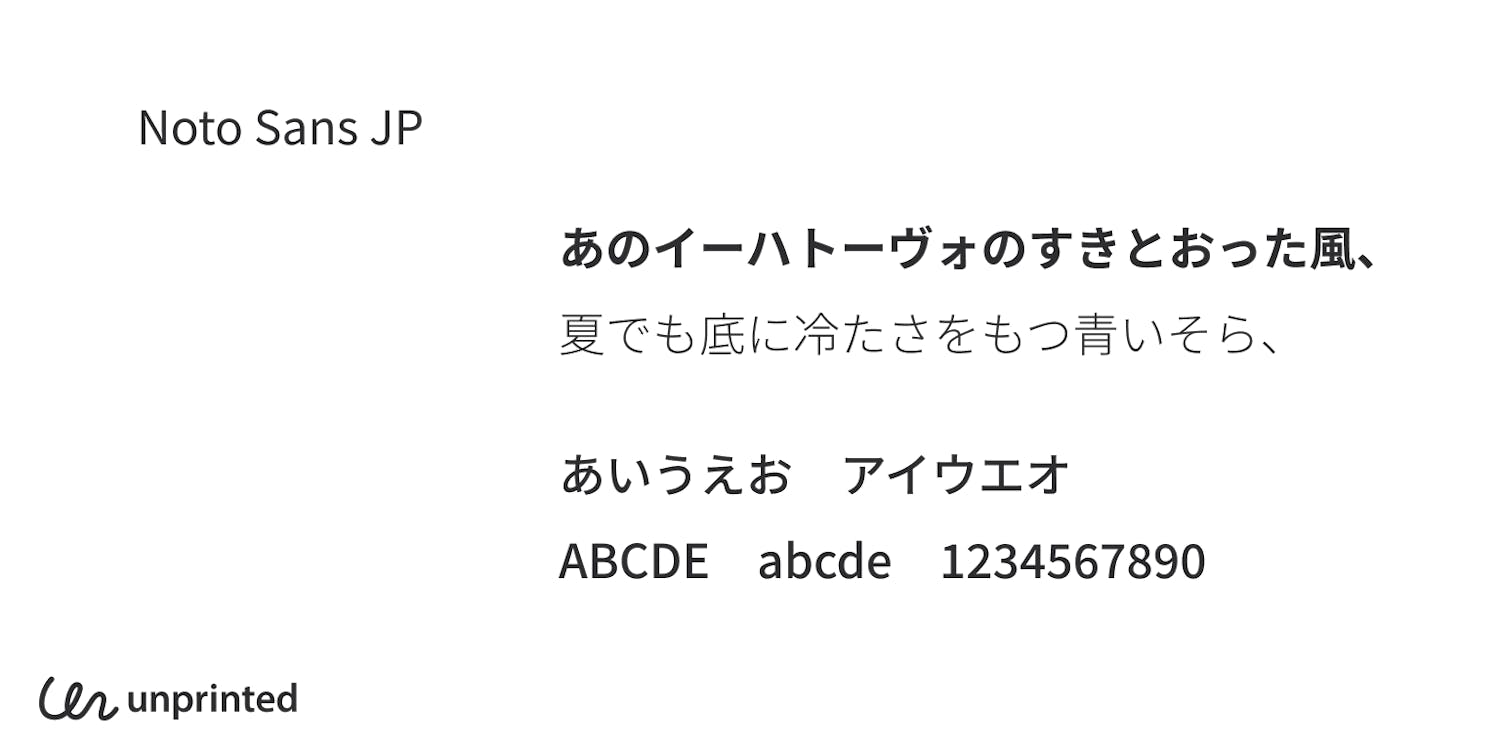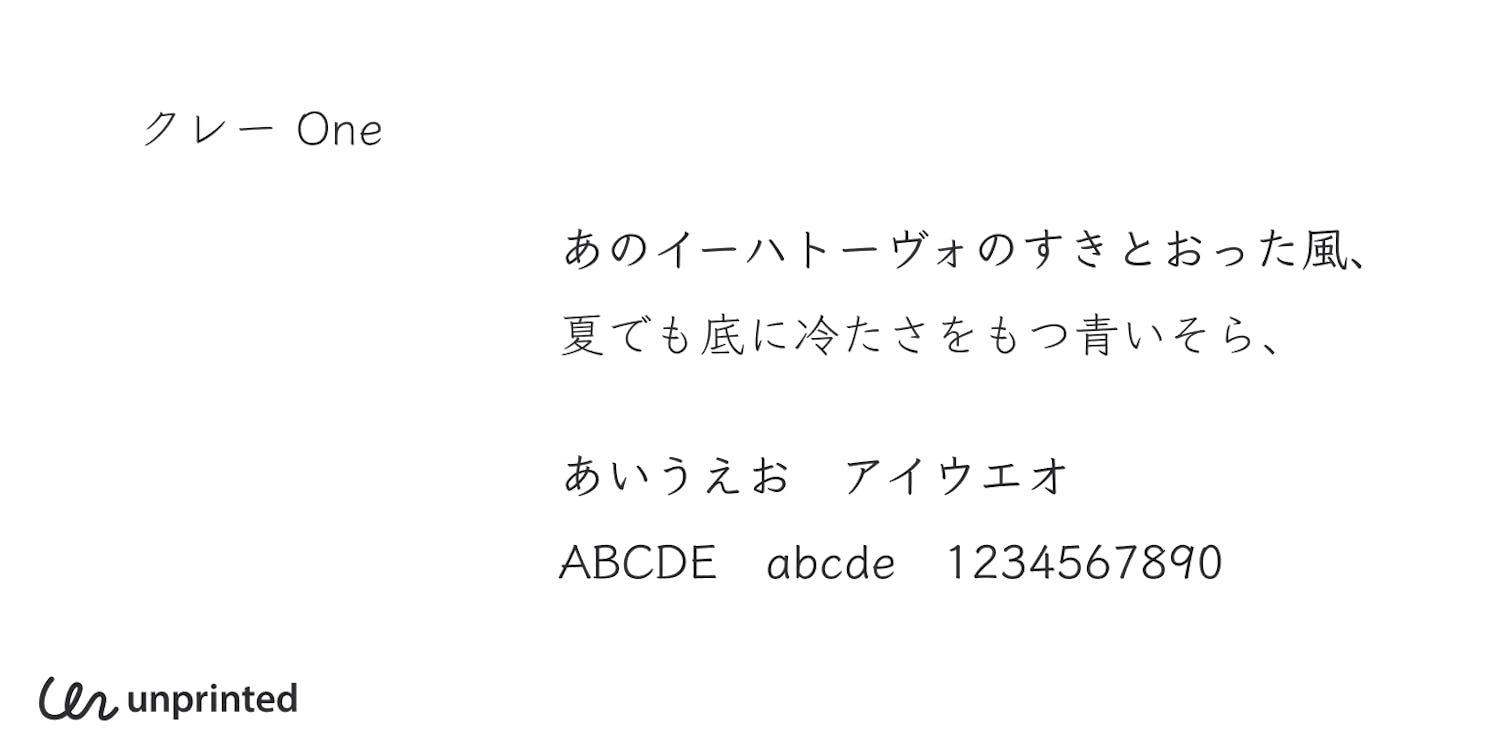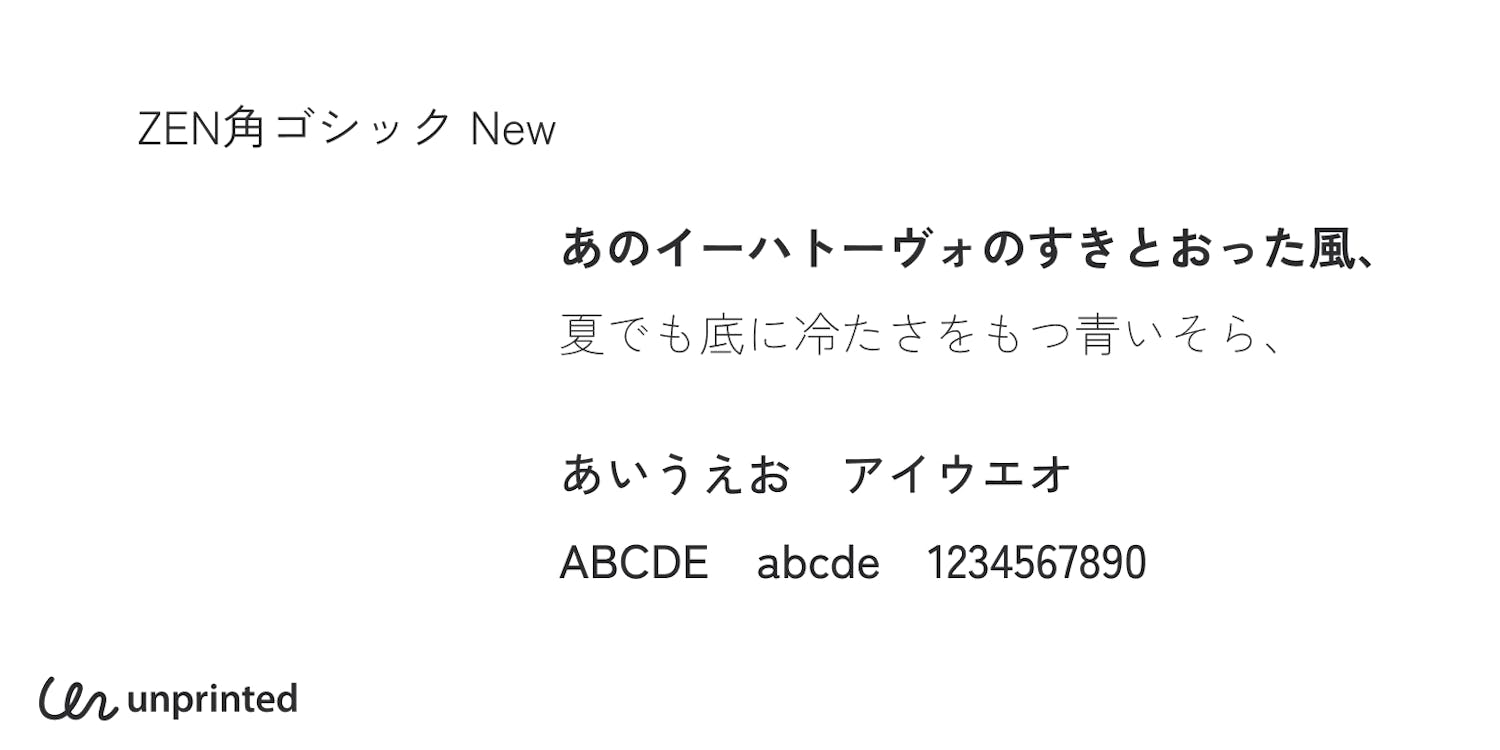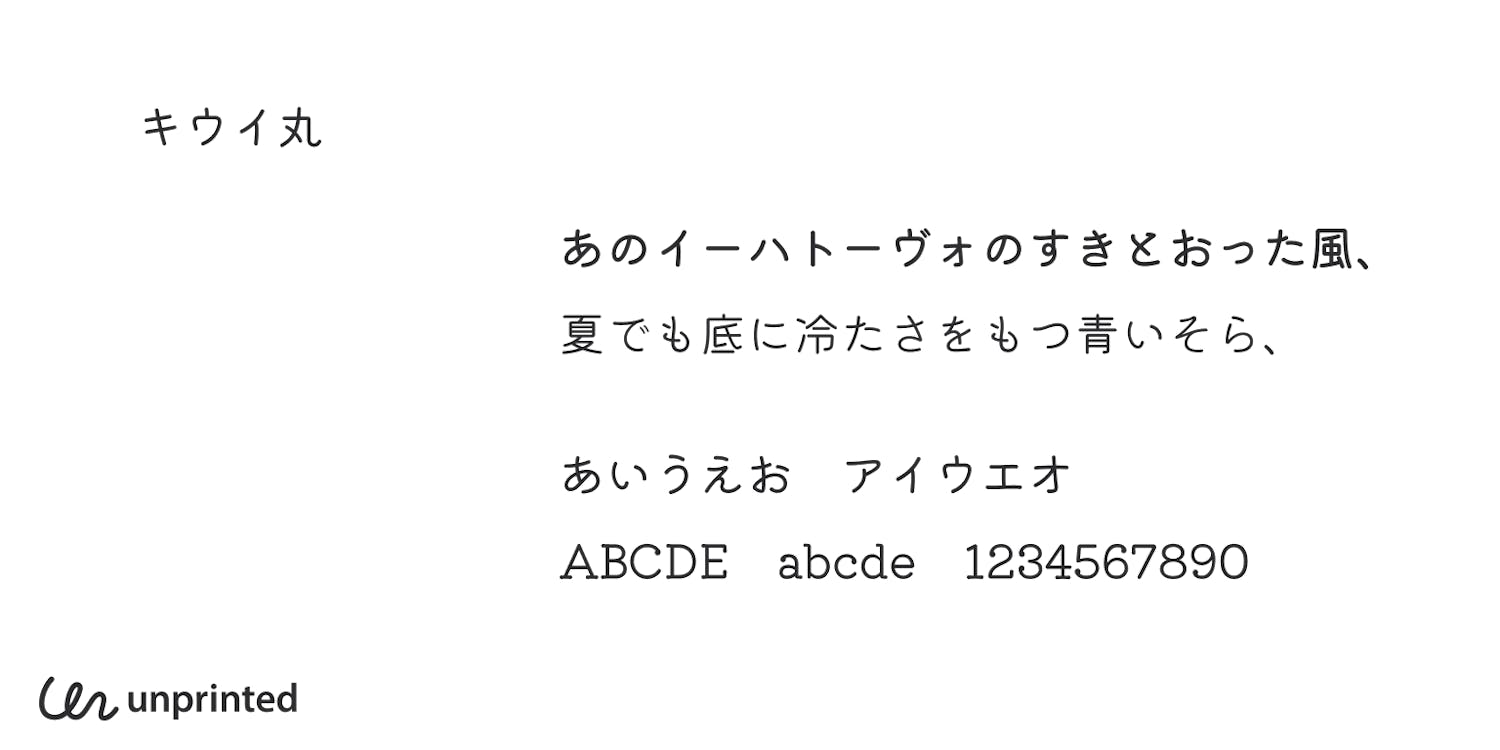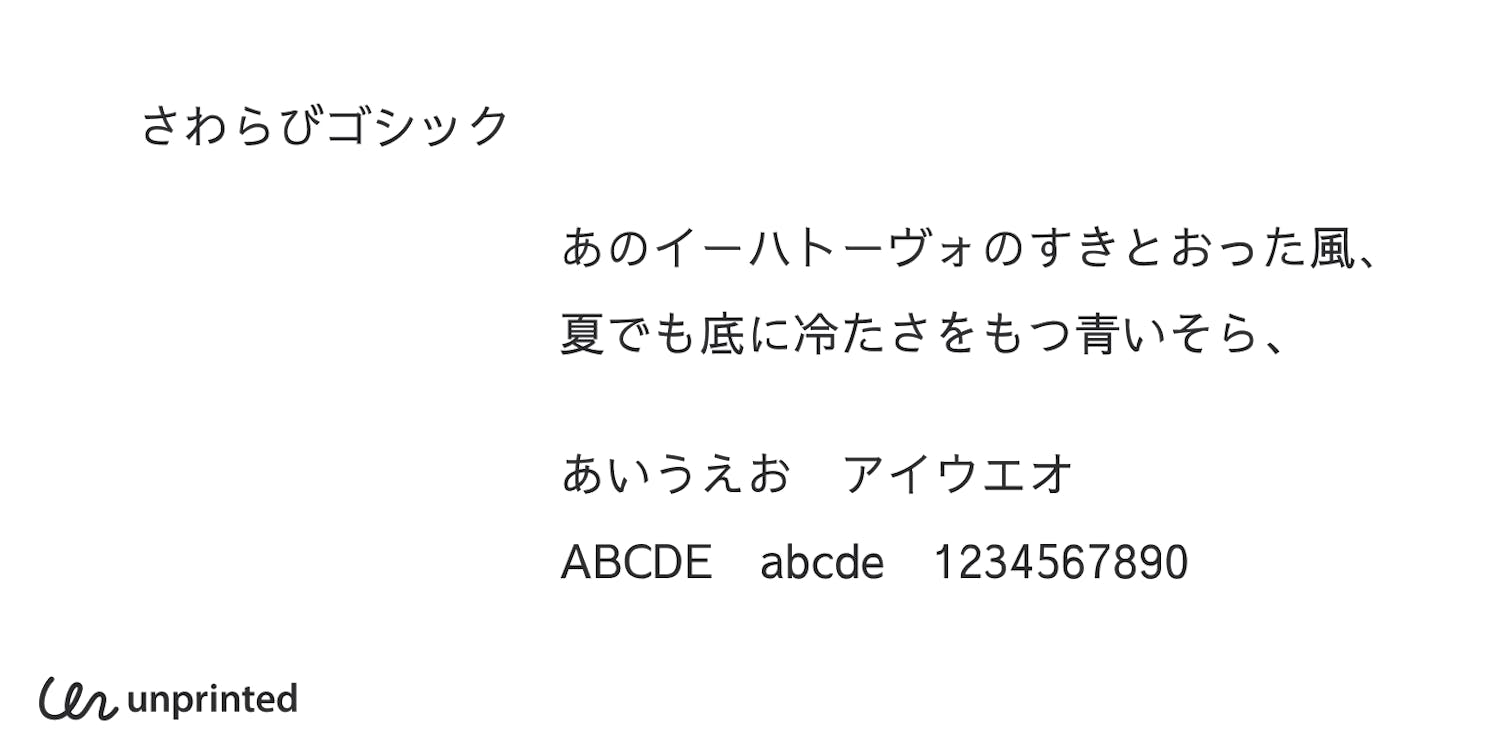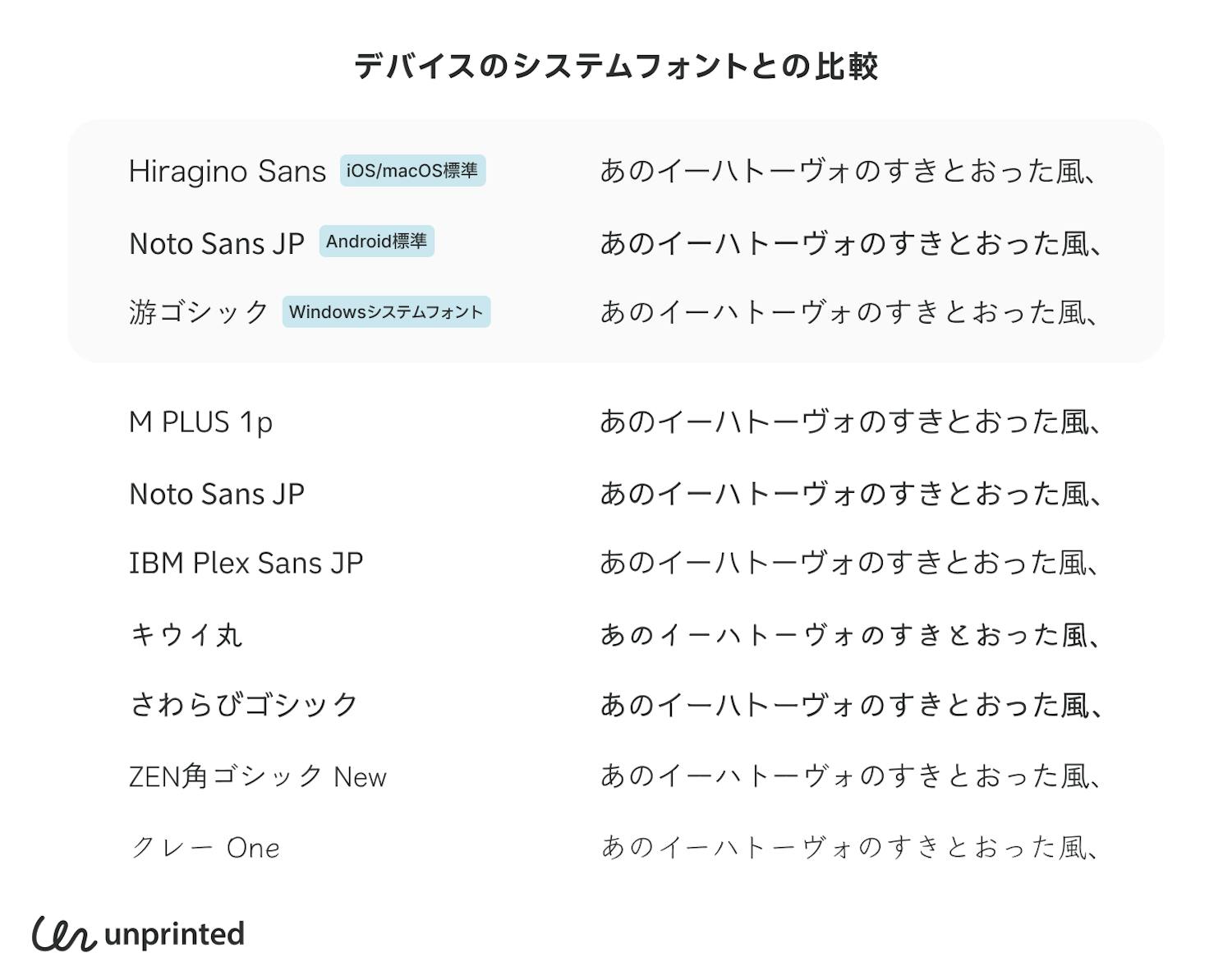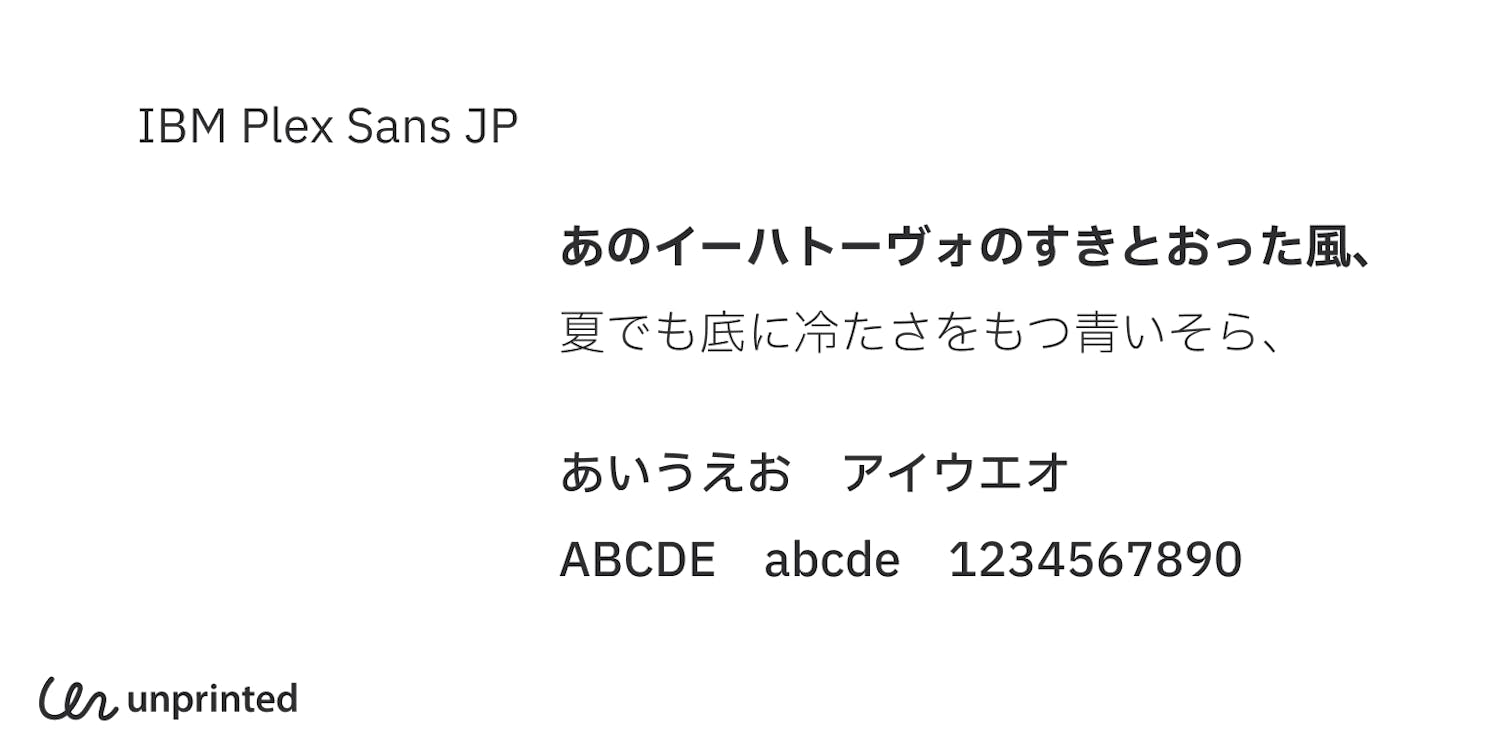
Google Fontsの使い方とWebフォントにおすすめの日本語フォント紹介!
近年はフォントのサブスクリプションサービス導入も増えて、さまざまな種類の日本語フォントをデザインに取り入れることが以前よりも容易になったのではないでしょうか?しかし、フォントファイルの配信が必要なWebフォントとしての利用には、サービス提供者によるサブスクリプションサービスの導入が必要となる場合もあり、クライアントワークなどでは導入が難しい場合も多いですよね。このような時にも、無料のGoogle Fontsで提供されているフォントであれば安心してデザインに取り入れることができます。この記事では、そんなGoogle Fontsの使い方をはじめ
• フォント自体の品質と利用実績
• WebサイトやWebサービスで利用できる汎用性の高さ
を主な観点としてWebフォントとしておすすめのGoogle Fontsをまとめました。
Google Fontsとは?日本語フォントも豊富なフリーフォントサービス
Google Fontsとは、Googleが提供する無料のWebフォントサービスで、商用利用可能なフォントがWebフォントとして無料で利用できることが特徴です。日本語のフリーフォントの種類も豊富で、デバイスフォント以外のフォントでWebデザインを行う際に便利な選択肢となっています。
それでは早速、Webフォントとしてサイトの見出しや本文での使用に最適なGoogle Fontsの日本語フォントを7種紹介します!
M PLUS 1p:幅広い用途をカバーする定番日本語フォント
M PLUS 1 P
ThinからBlackまでの7種類のウェイトや欧文フォントまでカバーしており、とても汎用性の高い日本語フリーフォント。見出しから本文までこれ一つでカバーすることができます。Google Fontsで配布されているのはM PLUSフォントの中でも最も標準的な「M PLUS 1p」となっていますが、公式サイトでは2種類の和文と3種類の欧文をそれぞれ組み合わせた6通りのスタイルで提供されています。
M PLUSの種類
また、M PLUSの最新版はGithub Pagesにて公開されており、こちらはM PLUS 1とM PLUS2の2種類のフォントとして提供されています。それぞれ、可変フォント (Variable fonts)として作られており、自由にフォントの太さやスタイルを変更することができます。
Noto Sans JP(源ノ角ゴシック):今一番使われているフリーフォント?
Noto Sans JP
Noto Sans JP(源ノ角ゴシック)はAndroidのシステムフォントとしても使用されており、優れた可読性からWebサイトをはじめとした大変多くのデザインで使用されている日本語フォントです。Noto Sansは、AdobeとGoogleが「全世界の言語に対応できるフォントを開発する」ことを目的として共同で開発したもので、さまざまな言語で表示ができるフォントとして多言語サイトでの使用も多いです。
IBM Plex Sans JP:IBMが開発した高品質な日本語フリーフォント
IBM Plex Sans JP
IBM Plex Sansは、もともとIBMがコーポレートフォントとして使用するために「人間と機械 」というIBMのテーマにもとづいて作成したもので、このテーマに共感する企業や個人がこのフォントを利用できるようにとオープンソース化されました。8種類のウェイトが提供されていることで、汎用性も高く、太いウェイトでも潰れない設計でWebデザインなどにもとても使いやすいです。前出のNoto Sansに比べて細部の曲線に丸みがあることで、より柔らかい印象を作りたい時などに使用するのも良さそうです。このWebメディアunprintedでもWebサイトの日本語フォントとしてIBM Plex Sans JPを採用しています。
キウイ丸:柔らかい印象の丸ゴシック体なら
キウイ丸
フリーフォントのマメロンをベースに作られており、Light, Regular, Mediumの3種類のウェイトが提供されているので、見出しから本文まで使うことができます。様々な媒体で目にする人気のフォント「秀英丸ゴシック」や「筑紫A丸ゴシック」を使いたいシーンでも代わりとして使用できそうで、子供向けや柔らかい印象のデザインととても相性が良いです。
さわらびゴシック:小さめの文字でも読みやすい本文向けフォント
さわらびゴシック
さわらびゴシックは、可読性に優れたスタンダートなゴシック体フォントです。小さめの文字でもつぶれにくいことが特徴で、本文での使用を想定されています。そのため、ウェイトはRegularのみとなっていますが、読みやすい文章をデザインしたいときにおすすめ。筆文字のような”とめ・はらい”のカーブがさりげなく表現されており、優美な印象が感じられ、いろいろなジャンルと相性が良さそうです。「DeNAxAI」のWebサイトでも日本語の文章に使用されています。
ZEN角ゴシック New:字面が小さく、ゆとりがある落ち着いた印象
ZEN角ゴシック New
ZEN角ゴシック Newは、ゆとりがある落ち着いた印象で本文を作りたい時に役立ちます。「日本女子大学のホームページ」などで使用されており、Zen角ゴシック Newで表現された文章はやや柔らかい印象を与えるのではないでしょうか?教育系や、オーガニック食品など信頼感を与えたいときにおすすめのフォントです。
クレー One:圧倒的な高級感と落ち着きを表現できるフリーフォント
クレー One
ここまでゴシック体の比較的ニュートラルな書体を紹介してきましたが、クレーは高級感や落ち着きを表現したい日本語本文のデザインで使える他、スクリーンフォントとしても人気のフォントです。フォントワークスが提供しているフリーフォントで、鉛筆で書いたような人間味と繊細さを持ちながらも教科書体のように読みやすいことが特徴です。RegularとSemi Boldの2種類が利用可能。
各OSのデバイスフォントとの比較
Webフォント使用する場合には、デバイスのシステムフォントを使用する場合と比べてサイトの読み込み速度の面でデメリットもあります。そこで、本文のフォントをWebフォントにするだけの価値があるのかというのは気になる点ですよね。ここでは、今回紹介したGoogle FontsのフォントをiOS/macOS, Android, Windowsのシステムフォントとの違いが分かりやすい形で並べてみました。
各OSのシステムフォントとおすすめのGoogle Fontsの比較
iOS/macOSの標準フォントであるHiragino Sansは可読性が非常に高く、ニュートラルな印象なので幅広いデザインで使用できます。同じような用途でデバイスに関係なく統一したイメージを作るには、同じく可読性に優れて癖の少ないIBM Plex Sans JPや、Androidの標準フォントでもあるNoto Sans JPが最初の選択肢となるでしょう。モダンな印象や個性を出したい時にはM PLUS 1pを使用してみるのがおすすめです。落ち着きを表現したい場合には、Windowsのシステムフォントである游ゴシックのように、文字周りに空間のゆとりがあるさわらびゴシックやZen角ゴシックNewを選択するのが良さそうです。このように、どのようなイメージを与えたいのか、ブランドのコンセプトに合わせてWebフォントを選んでみると、デザインがもっと楽しくなりそうですね。